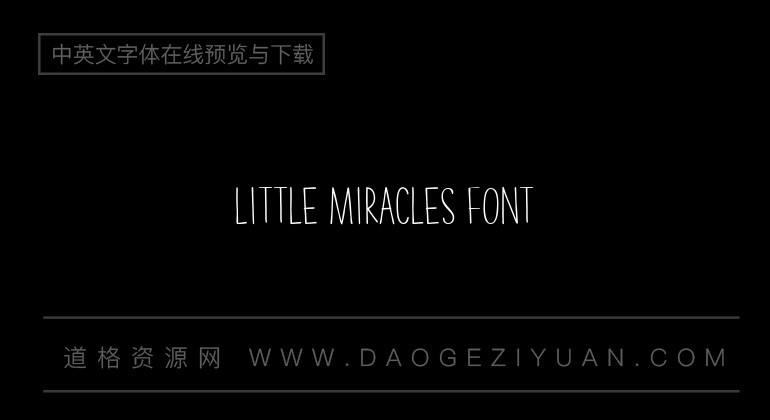
Little Miracles Font
Little Miracles Font 是一款手写风格的字体,具有自然、欢快、可爱的特点。它是由设计师 Balpirick 设计,于 2019 年发行。 这款字体包含了大写字母、小写字母、数字、标点符号、以及一些特殊字符。它的字母呈现出自然的手写风格,每个字母都有独特的笔画和形状。与此同时,该字体的字间距、字母大小和字母间距都经过精细的调整,使得整体的排版效果更加美观。 Little Miracles Font 的用途很广泛,可以用于卡片、海报、包装设计、儿童书籍、标识和徽标等多种设计场景。无论是作为标题还是正文,它都能够为设计作品增色不少。此外,该字体可以与其他字体进行搭配,创造出更加多样化的设计效果。
Little Miracles Font是一款非常不错的手写艺术字体,具有很好的视觉感,适合于文化类的宣传设计、商业类品牌的广告和产品包装设计以及个性化文字排版等较多场景。